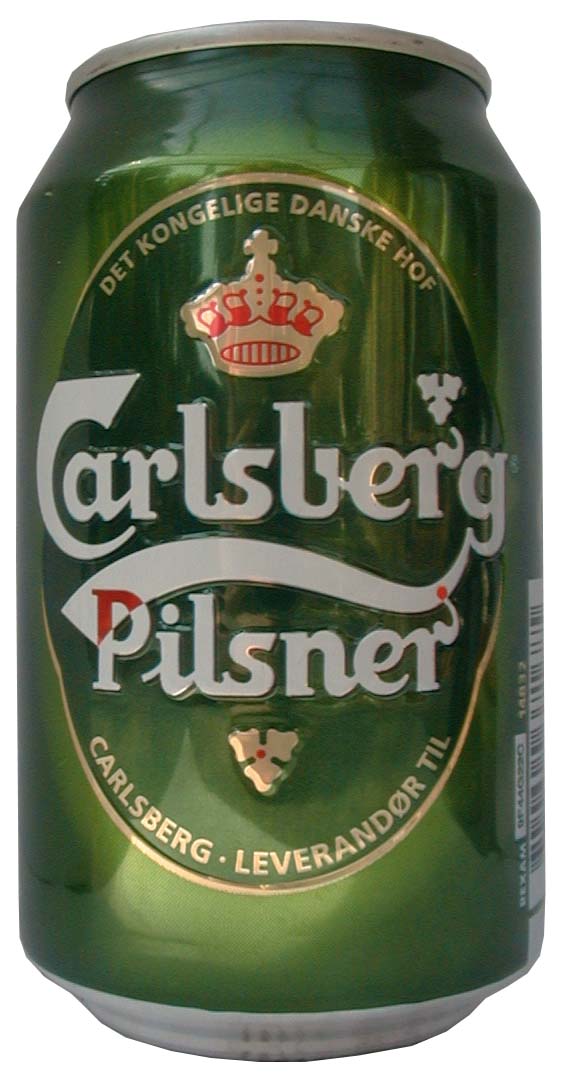
Hallo Leute, brächte mal wieder eure hilfe und zwar braucht oder will ein Kunde von mir seiner Tocher umbedingt ein T-Shirt mit ihrem Namen schenken und er will dafür auch nur diese eine CARLSBERG schrift haben !!
Kann mir einer sagen was das für eine ist ?!
Nunja, das ist kein digitaler Font, das ist ein handgemachtes Logo von Thorvald Bindesbøll, 1904 gezeichnet. Siehe hier oder hier.
Natürlich könntest du zB die Ballpark Script ausprobieren als Ersatz dafür. Oder mal sehen ob die Prater Script ein ähnliches Gefühl auslöst. Vielleicht auch die Deftone Stylus oder die Forelle als Freefonts. Nur so ins Blaue hinein. Hab diese Varianten jetzt nicht abgecheckt.
Auch Ilse Carlson wäre nicht allzu schwierig.
Aber im ernst: ich denke selber zeichnen ist da die einfachste Lösung.